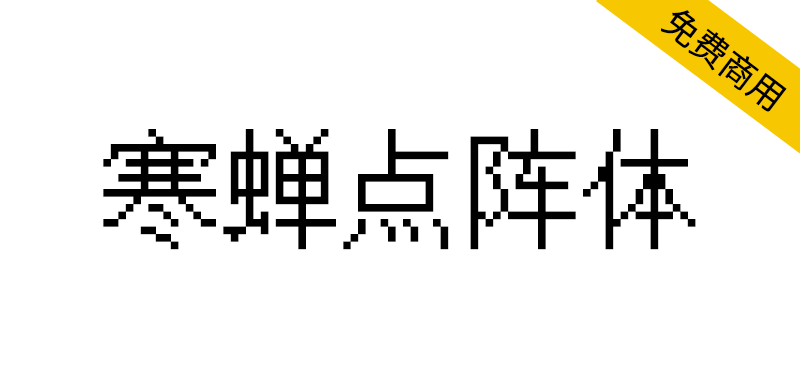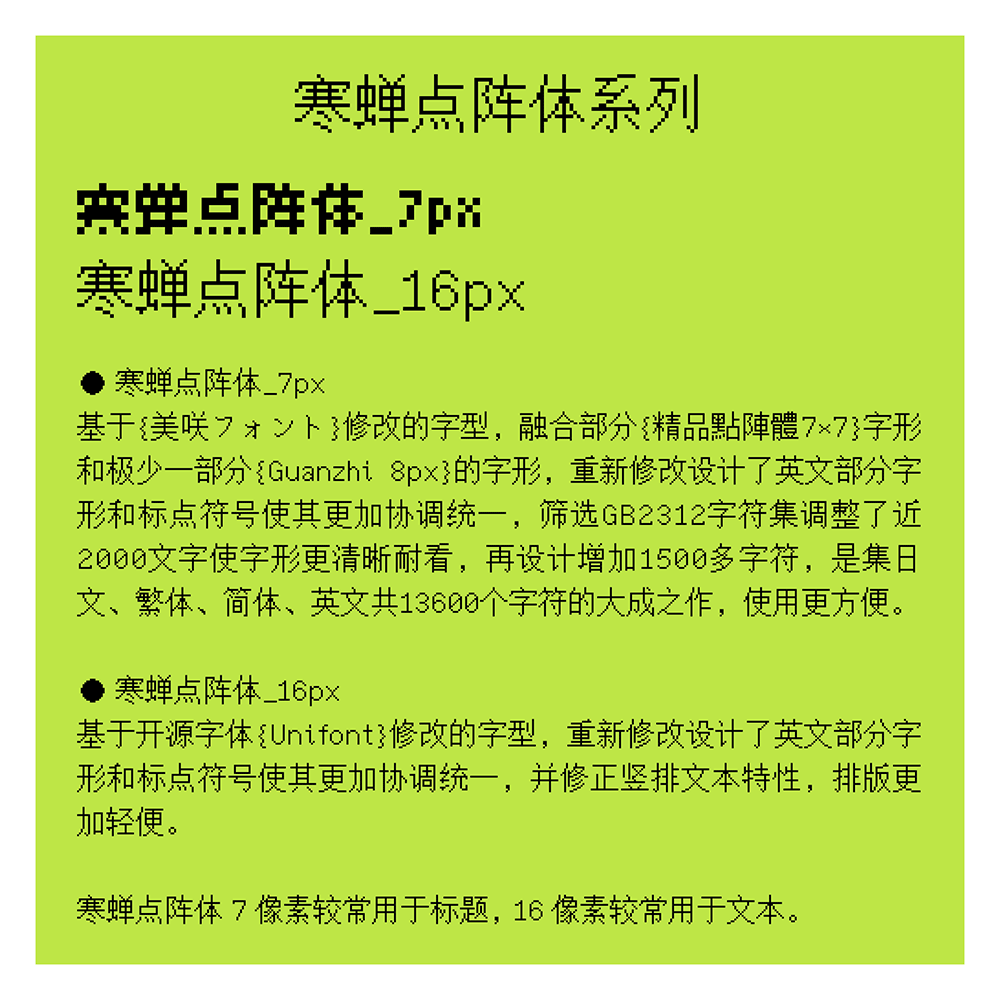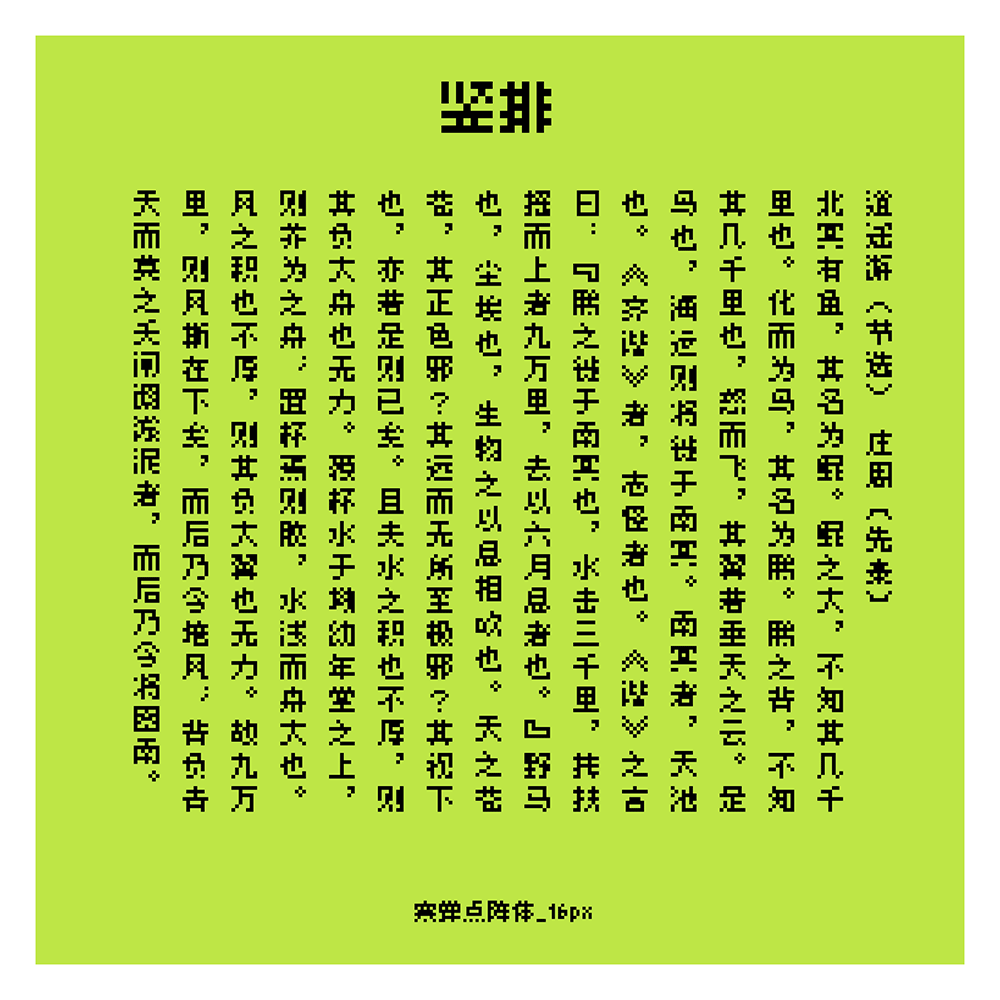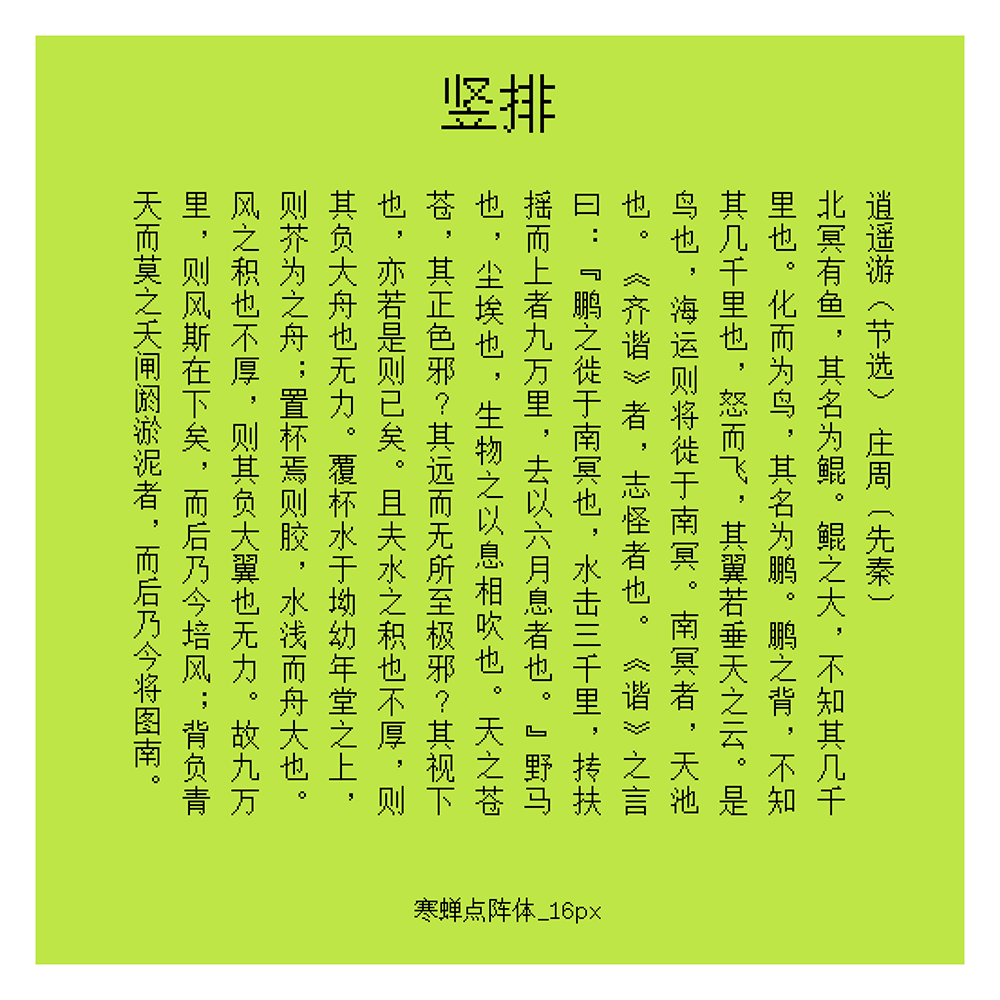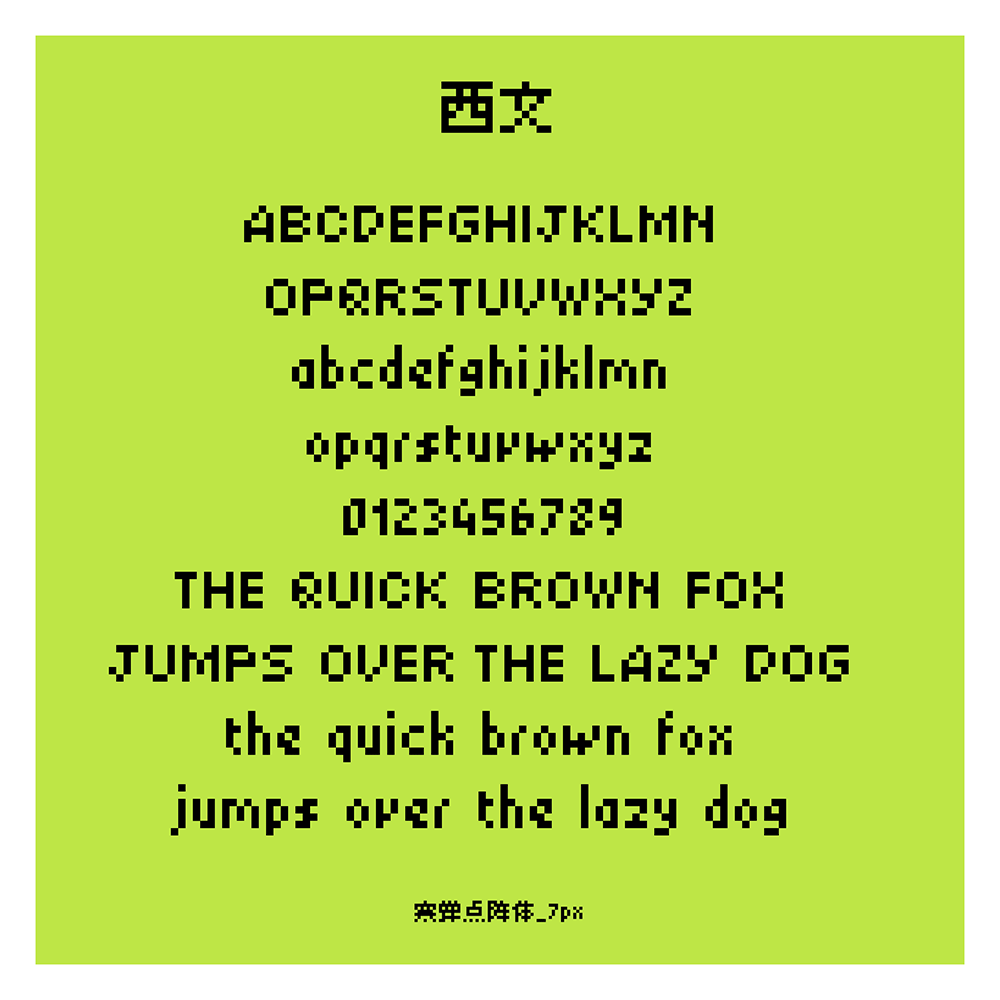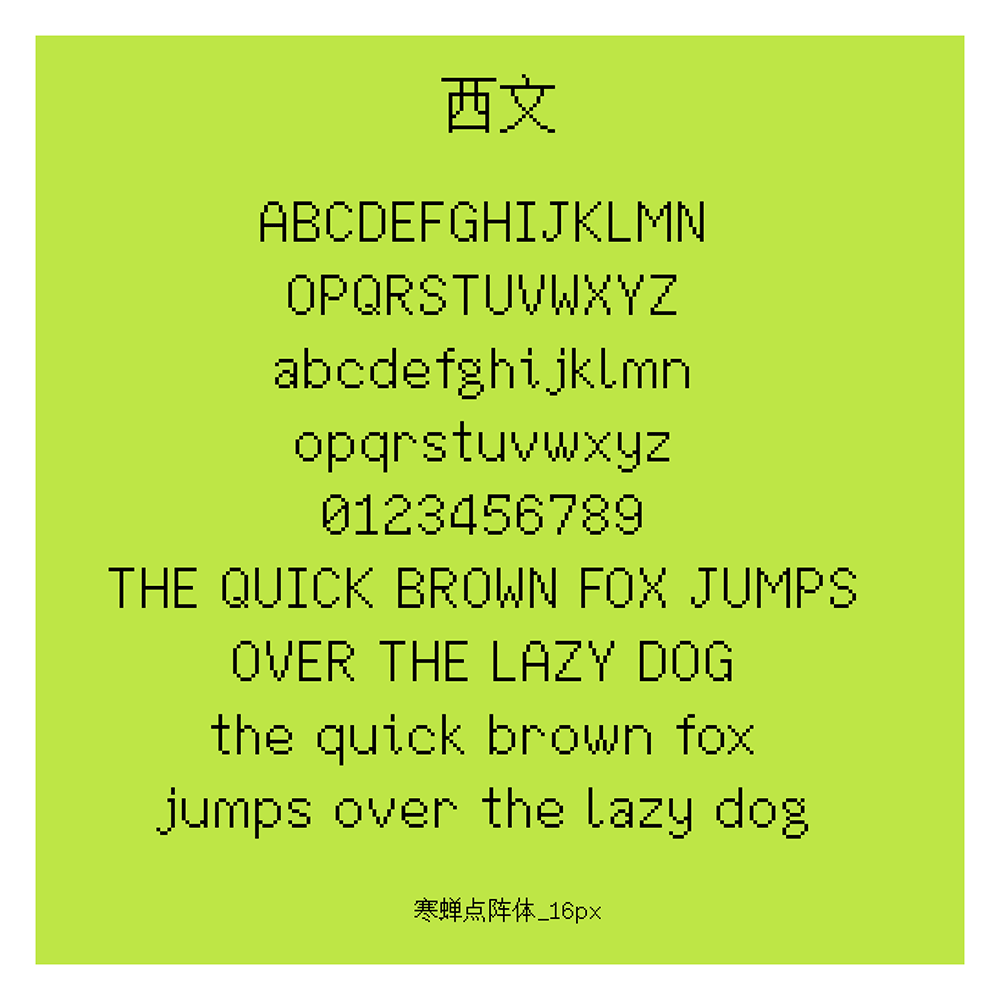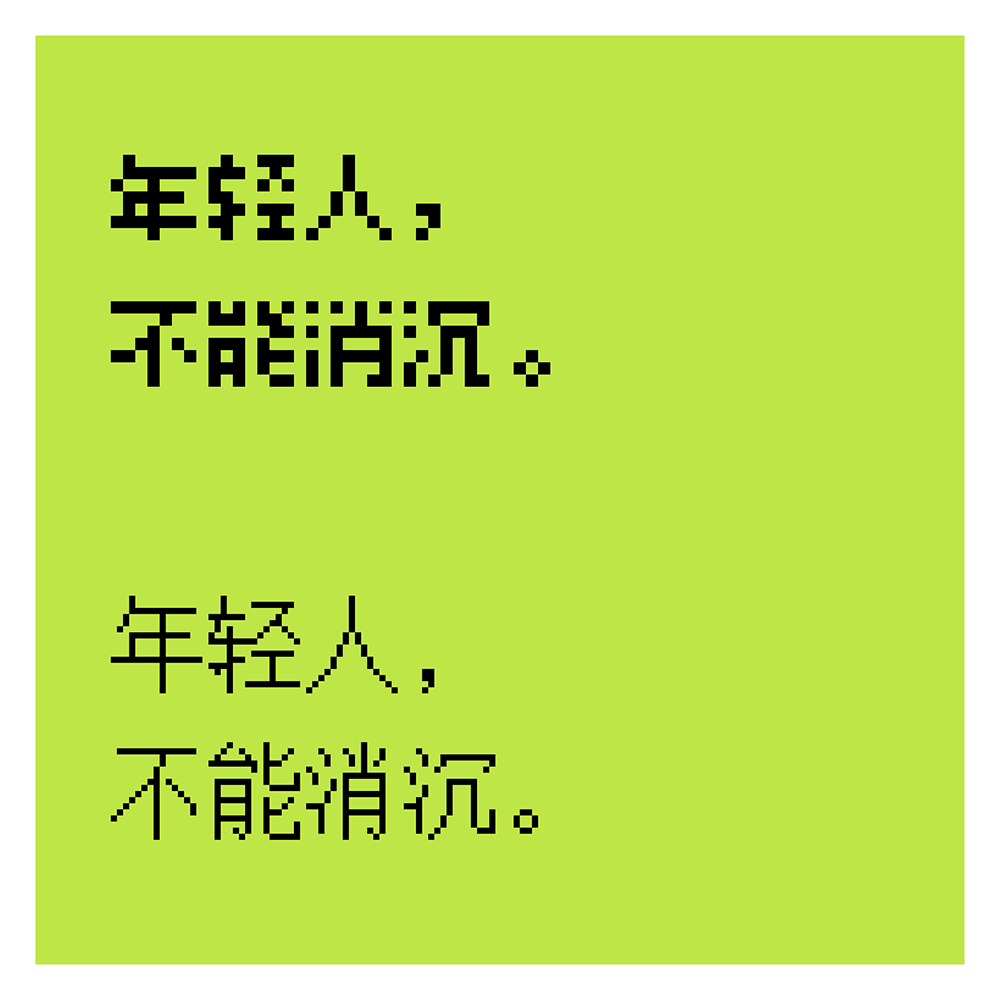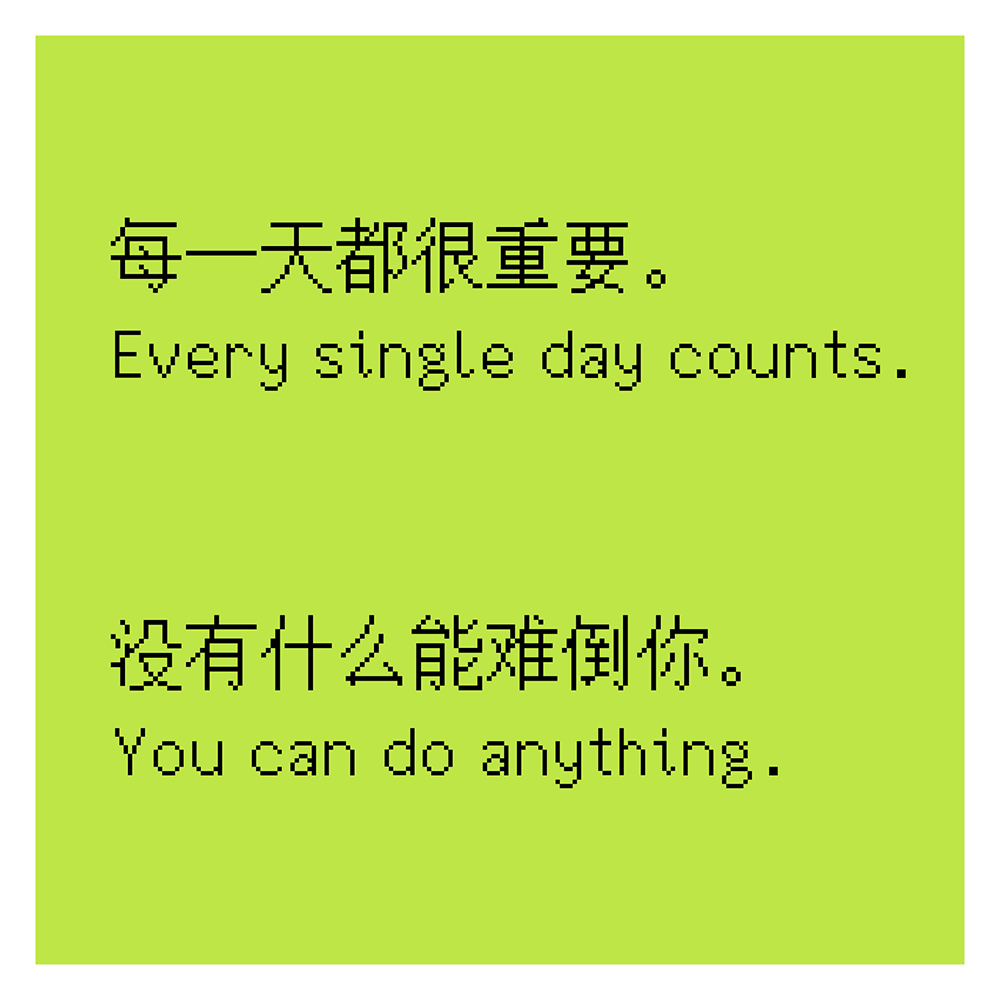
寒蝉点阵体 7px:基于美咲フォント修改的字型,融合部分精品点阵体7×7字形和极少一部分Guanzhi 8px的字形,重新修改设计了英文部分字形和标点符号使其更加协调统一,筛选GB2312字符集调整了近2000文字使字形更清晰耐看,再设计增加1500多字符,是集日文、繁体、简体、英文共13600个字符的大成之作,使用更方便。
寒蝉点阵体 16px:基于开源字体Unifont修改的字型,重新修改设计了英文部分字形和标点符号使其更加协调统一,并修正竖排文本特性,排版更加轻便。